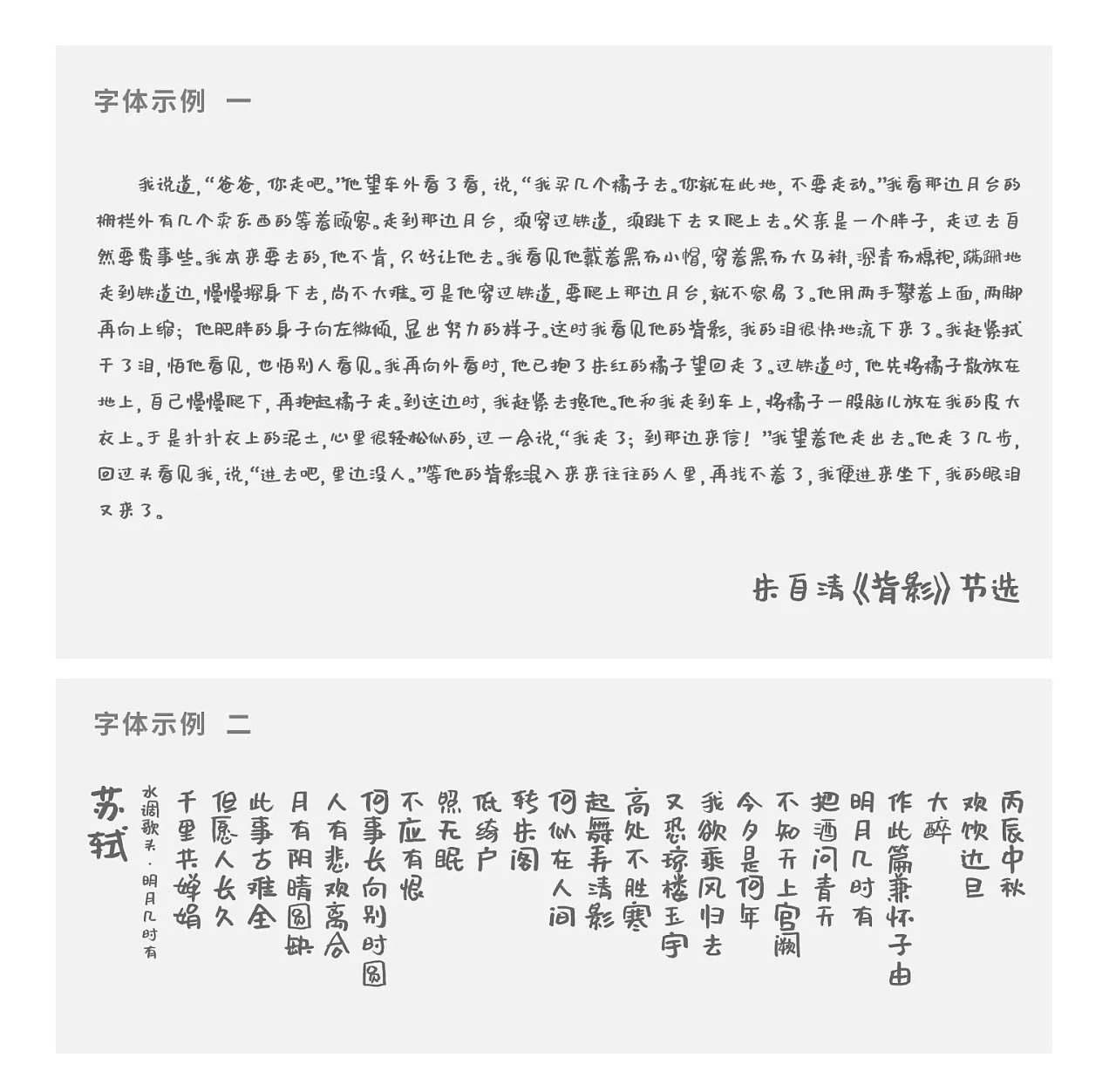
沒有華麗的創作過程介紹,因為他的確是用筆寫成,只有一個簡單的故事“一對戀人互為彼此相愛併為愛的結晶(女兒)而製作的一款手寫的中文字體”,這是送給女兒的禮物,也是送給大家的字體,寫壞約二十支軟頭毛筆,完成了六千多個字。
我的成長經歷中,沒有刻意練過手寫字。不過,在手寫海報方面倒是有一段經歷。和現在的直接噴繪印刷不同,學生時代經常需要手寫海報,經常一式多份。
原本是需要用馬克筆寫POP字,但是畢竟馬克筆對於我的學生時代來說,價格很昂貴,於是大家都用排筆+廣告色的方式進行創作。與傳統的中文書法楷隸行草不同,這種書寫方式可以把字寫得較為可愛,也算是一種更加手寫化的廣告字體。
後來在創作漫畫類作品的過程中,我發現這種字體也很適合用於休閒漫畫、插畫,於是在排筆書寫的基礎上逐漸變成了用中性筆書寫,並堅持了較長時間,也逐步有了自己的書寫風格。
在從事平面設計的工作中,經常需要手寫字,我發現楷隸行草之類的字體較多,較為休閒可愛的字體較少,好看的幾款都有較為嚴格的版權限制,設計師使用時需要較高的門檻。
因為七月恰好是女兒週歲生日,就用女兒名字拼音來命名,叫做“Muyao”,字母命名是方便兼容各類軟件。因為是用軟頭毛筆寫的,全名就叫做:沐瑤軟筆手寫體。
我和妻子是因為寫字認識的,也算是因字結緣。創作這套字,也希望能結識更多的朋友,希望能夠拋磚引玉,激發更多朋友能夠創作大神級的作品。
沐瑤軟筆手寫體比較休閒可愛,適合用於休閒漫畫、插畫。